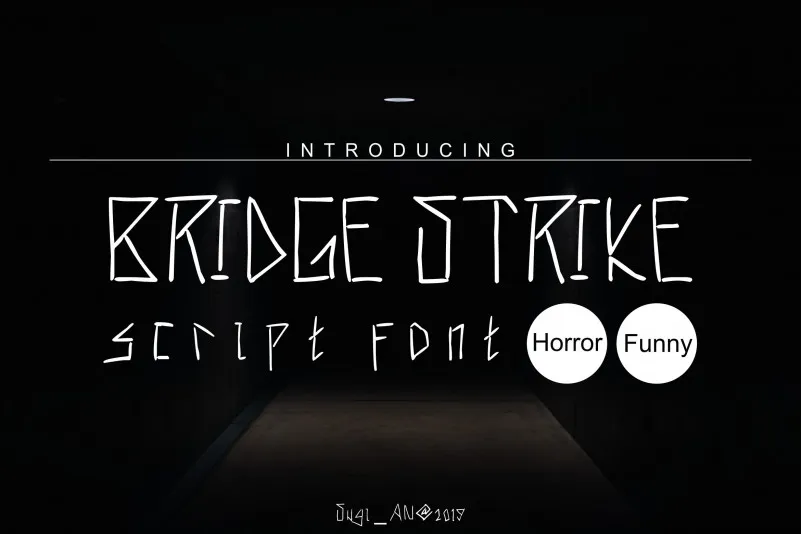
Bridge Strike Script Font – Download Grátis
Bridge Strike Script Font é uma fonte inovadora criada pelo designer Sugi_AN. Ela resulta de sua habilidade única para transformar a mão na criação de uma fonte, gerando um resultado que parece tanto assustador quanto divertido. Ideal para uso em design gráfico, seja ele corporativo ou personalizado, essa fonte oferece um tom único que certamente se destaca dos padrões tradicionais. Sua versatilidade permite usos inesperados e criativos em diferentes projetos de arte digital, fazendo dela uma opção ideal para aqueles buscando algo diferente na fontes de签字。Bridge Strike Script Font é mais do que simplesmente um recurso gráfico; ela é a assinatura perfeita para quem procura por algo único e vibrante no seu próximo projeto.